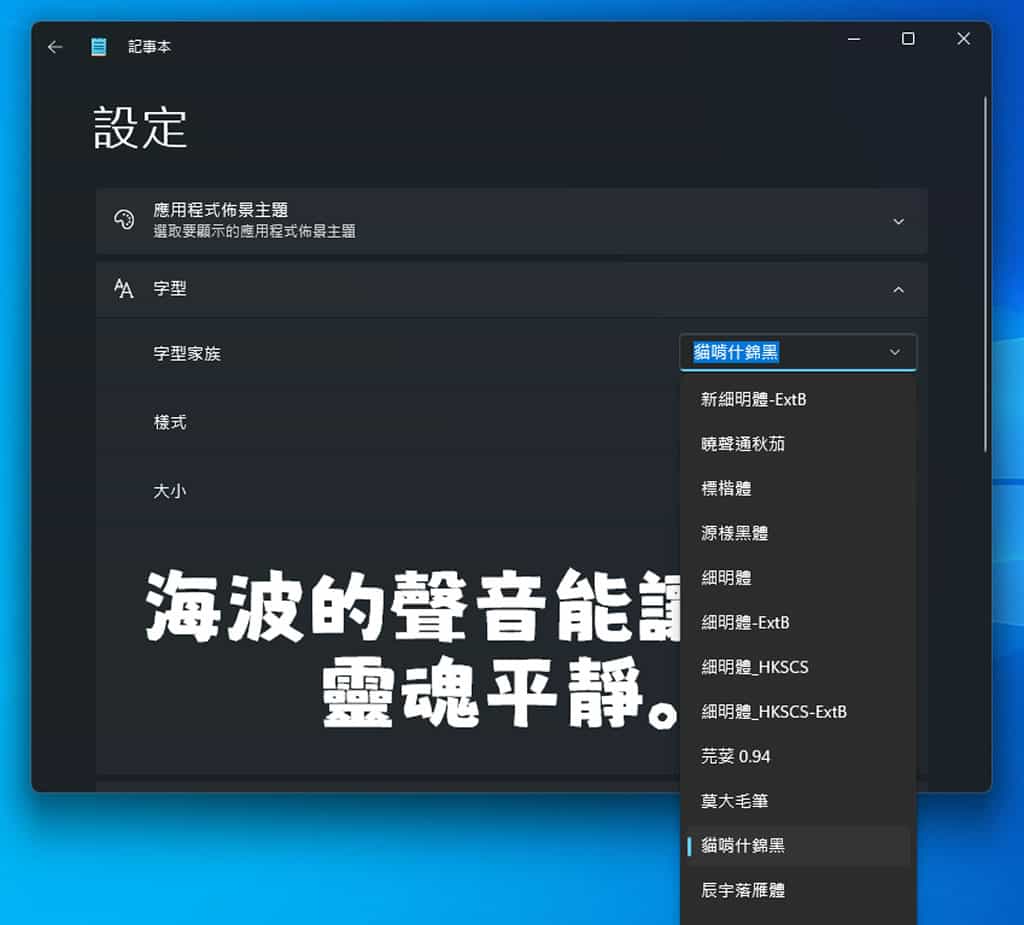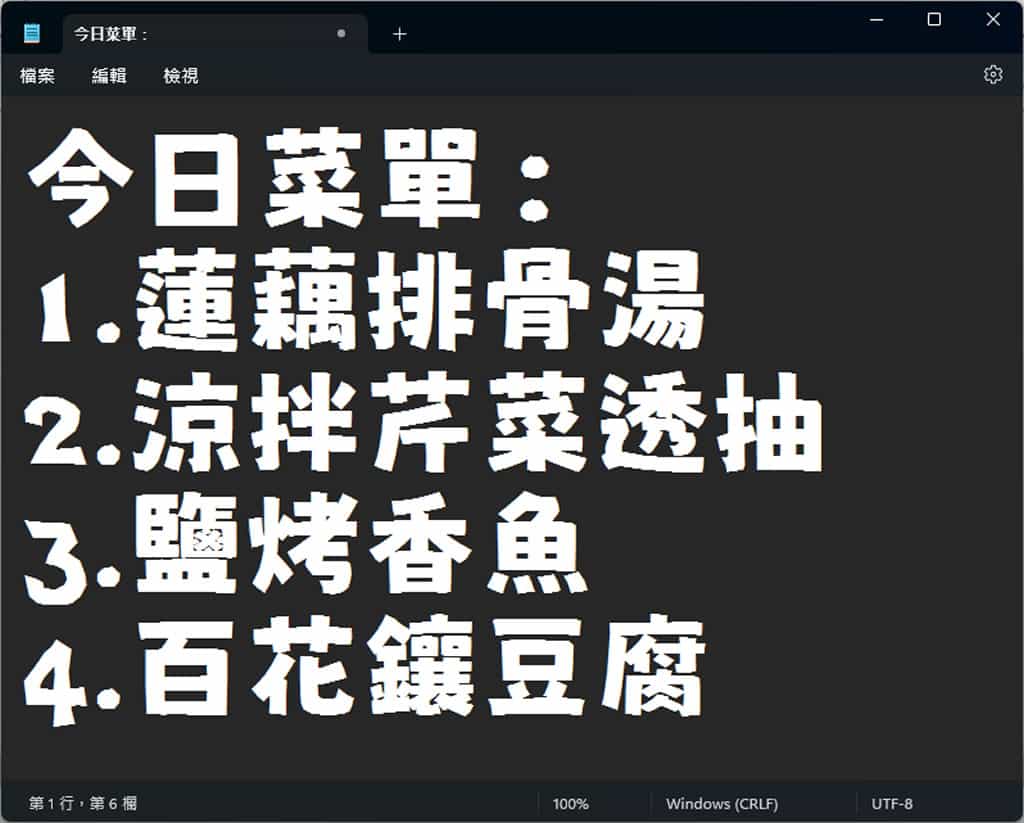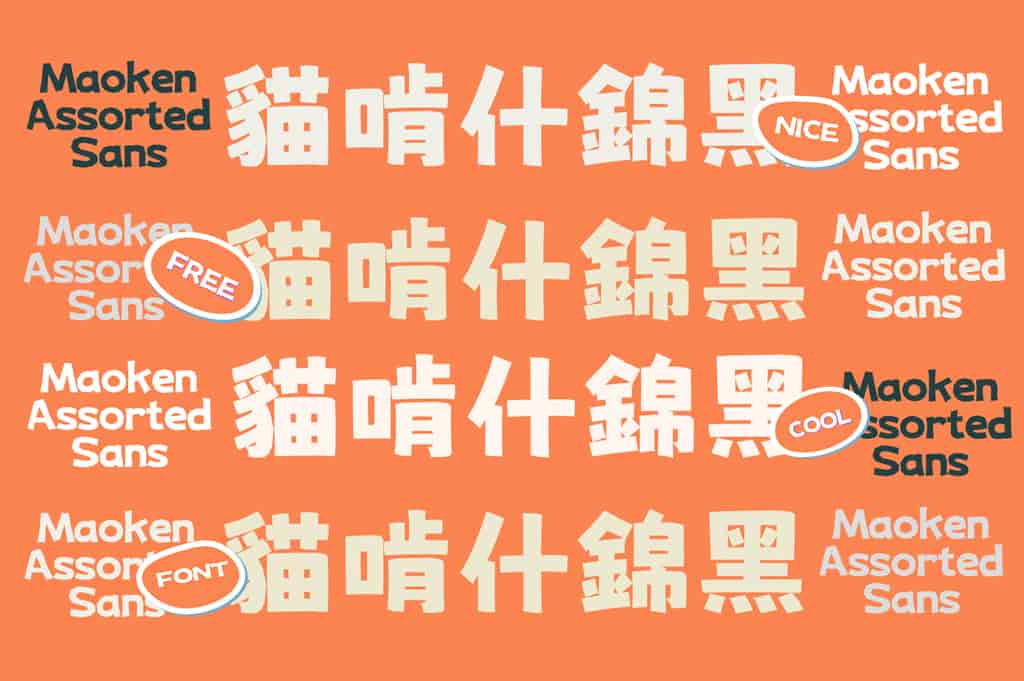
貓啃什錦黑(Maoken Assorted Sans-TC)是一個免費開放原始碼的繁體中文字體,主要改作自日本作者波間のかけひき創作的「にしき的フォント」(Nishiki-teki)字型。此字體根據《常用國字標準字體表》與 jf 7000 當務字集等多種來源,增補了繁體中文常用字,並針對部分漢字筆劃進行最佳化與修改,保留了日文字體的原有風格,以更符合中文使用者的需求。字體採用麥克筆手寫風格,筆劃活潑生動,呈現出可愛且有趣的視覺效果,非常適合用於海報或宣傳品的設計中,能有效吸引視覺焦點。此外,貓啃什錦黑採用 SIL Open Font License 1.1 授權,允許免費下載並自由使用,無須告知或標示原作者,亦可用於商業用途。
改作自日文字型的中文字型,麥克筆手寫風格,適合海報設計,可商業應用
4.字體具有麥克筆手寫風格,非常適合海報或宣傳品的設計。